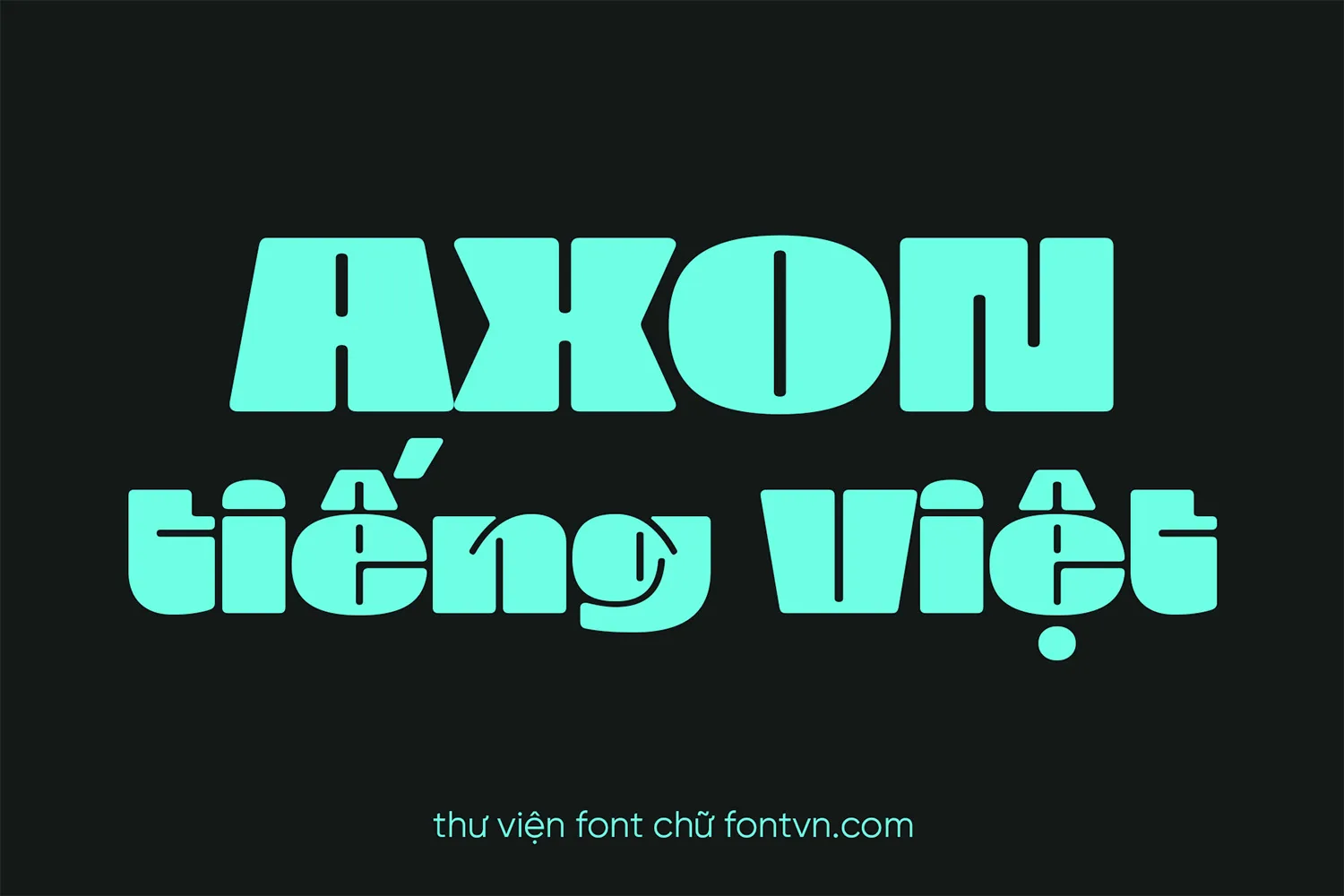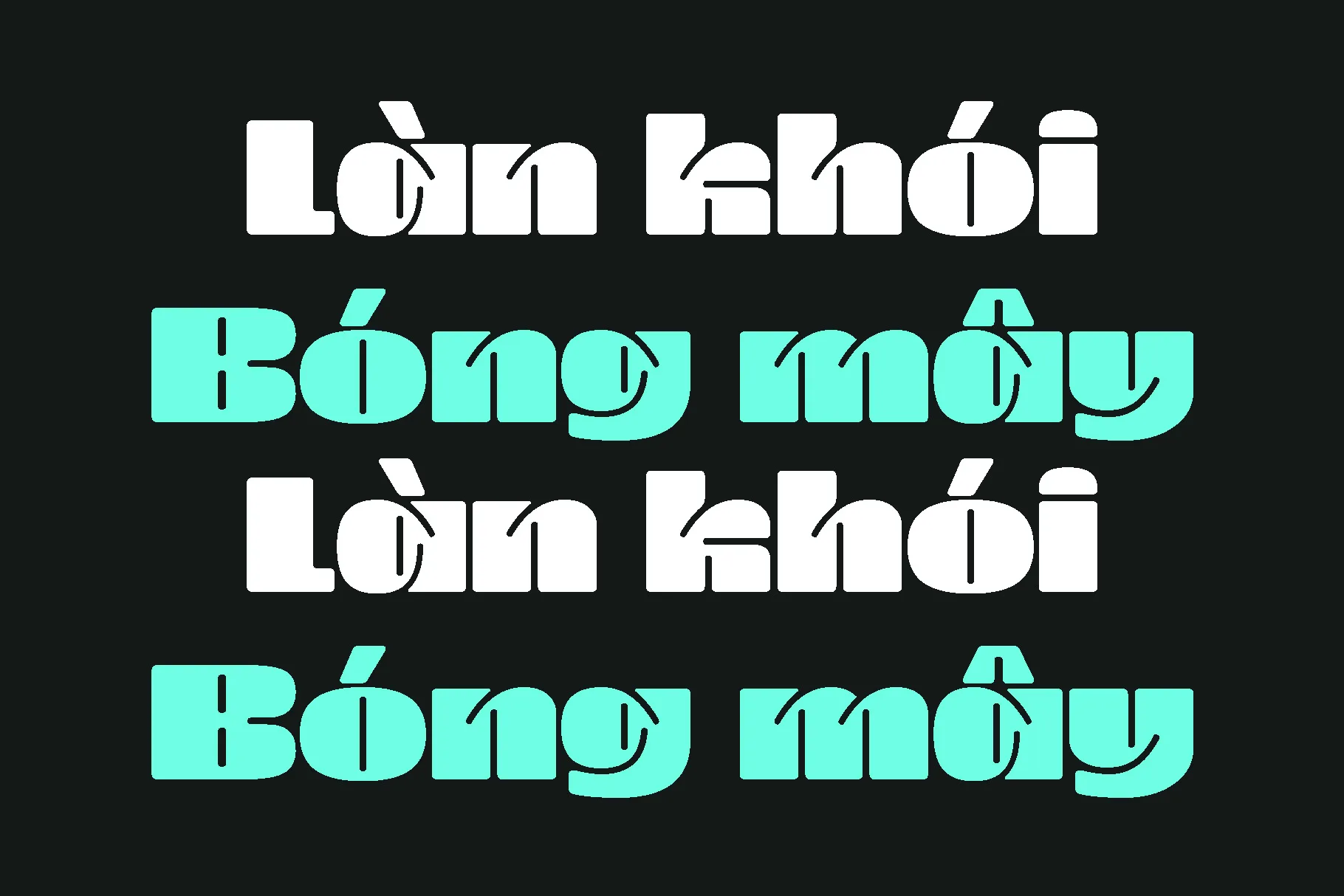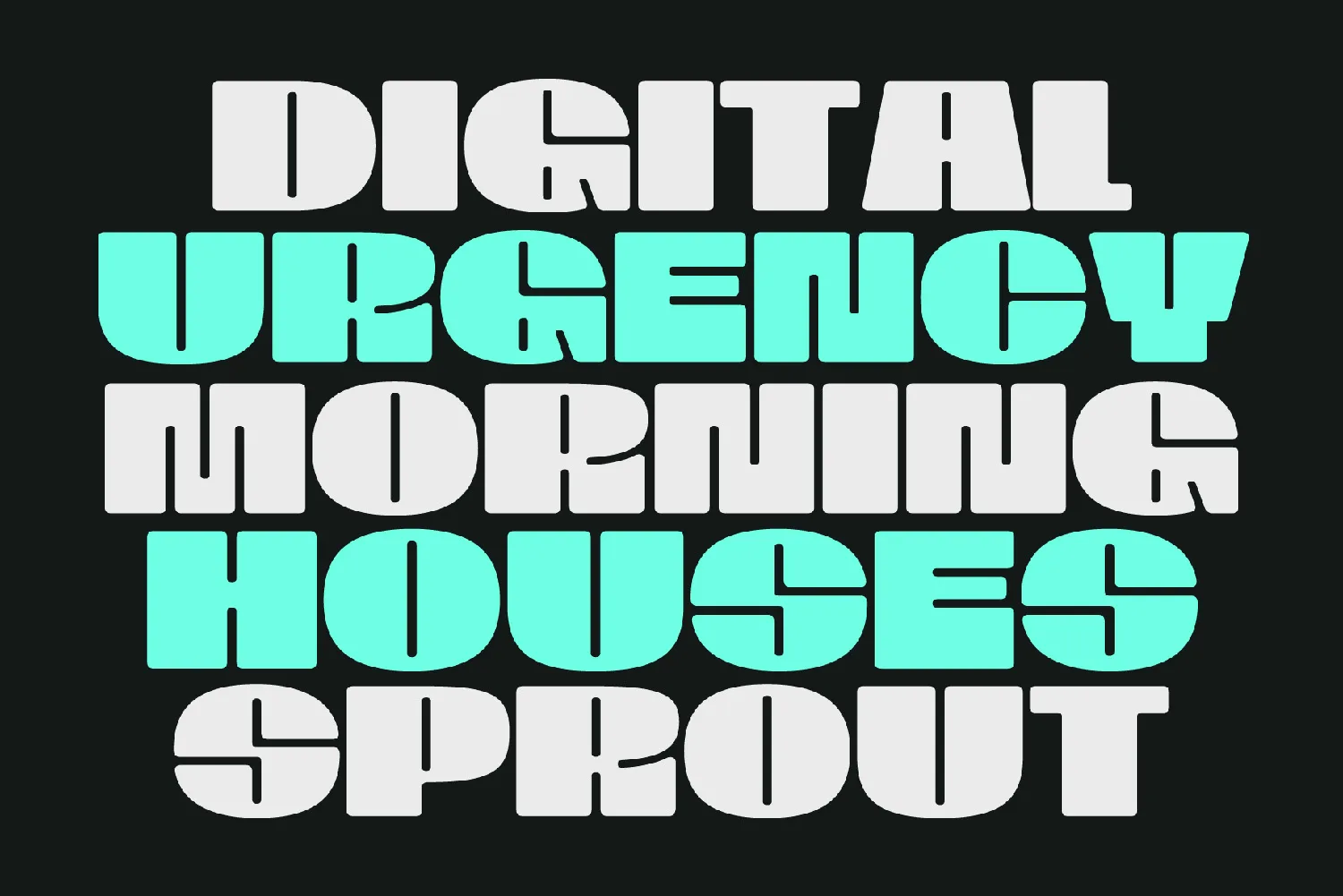
DVN AXON tiếng Việt – Font chữ đậm gây sự chú ý
DVN AXON là font chữ đậm, mạnh mẽ và hiện đại, được thiết kế để tạo ấn tượng ngay từ cái nhìn đầu tiên. Các nét chữ dày, chắc, kết hợp chi tiết cắt khe gọn gàng mang lại cảm giác công nghệ, năng động và rất “bắt mắt”.
Font phù hợp cho tiêu đề, poster, banner quảng cáo, logo, thumbnail, UI game và các thiết kế cần sự nổi bật. Hình khối rõ ràng giúp DVN AXON giữ được độ dễ đọc tốt ngay cả khi sử dụng ở kích thước lớn.
DVN AXON hỗ trợ đầy đủ tiếng Việt, dễ phối với các phong cách thiết kế hiện đại, tech, esport hoặc branding trẻ trung – là lựa chọn lý tưởng khi bạn muốn truyền tải sự mạnh mẽ và thu hút thị giác.